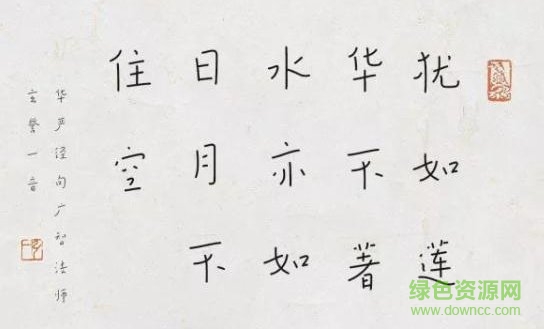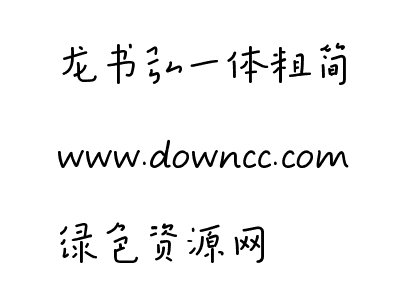
龍書弘一體粗簡是有龍書字庫推出的硬筆手寫字體,字跡優(yōu)雅隨意,給人佛系的清雅和淡然,給人古典韻味和出色的視覺效果,綠色資源網(wǎng)誠意推薦!
相傳伏羲氏時(shí),有龍負(fù)圖出河。因以龍紀(jì)事,創(chuàng)立文字,稱龍書!
以弘一法師書法字為基礎(chǔ)。采用最新設(shè)計(jì)方法;將這位佛法師的字與精神再次展現(xiàn)在了眾人面前。全部字形分粗細(xì)兩款。
弘一法師的前半生是名喚李叔同的翩翩濁世佳公子,他是世間最懂書法的音樂家也是最懂音樂的書法家。